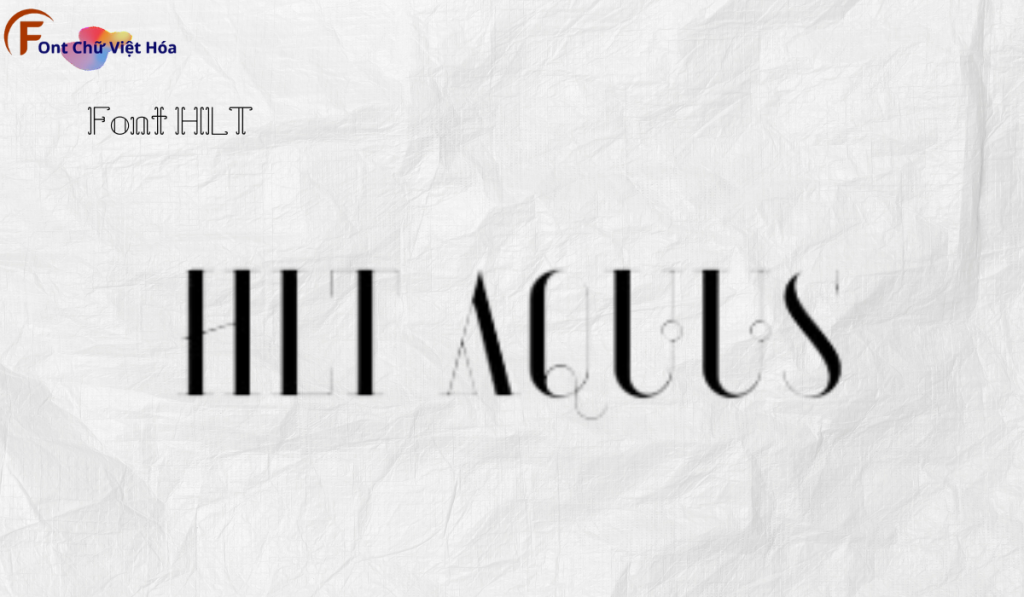
Font HLT Aquus Việt Hóa
Tác giả: HLT
Font HLT Aquus Việt Hóa là một font chữ không chân mạnh mẽ, thuộc bộ font HLT. Được thiết kế với mục tiêu mang lại sự nổi bật và ấn tượng, font này lý tưởng cho các dự án thiết kế như tiêu đề, quảng cáo, và bao bì sản phẩm. Với các nét chữ đậm và chắc chắn, Font HLT Aquus Việt Hóa không chỉ dễ đọc mà còn tạo cảm giác mạnh mẽ và quyết đoán.